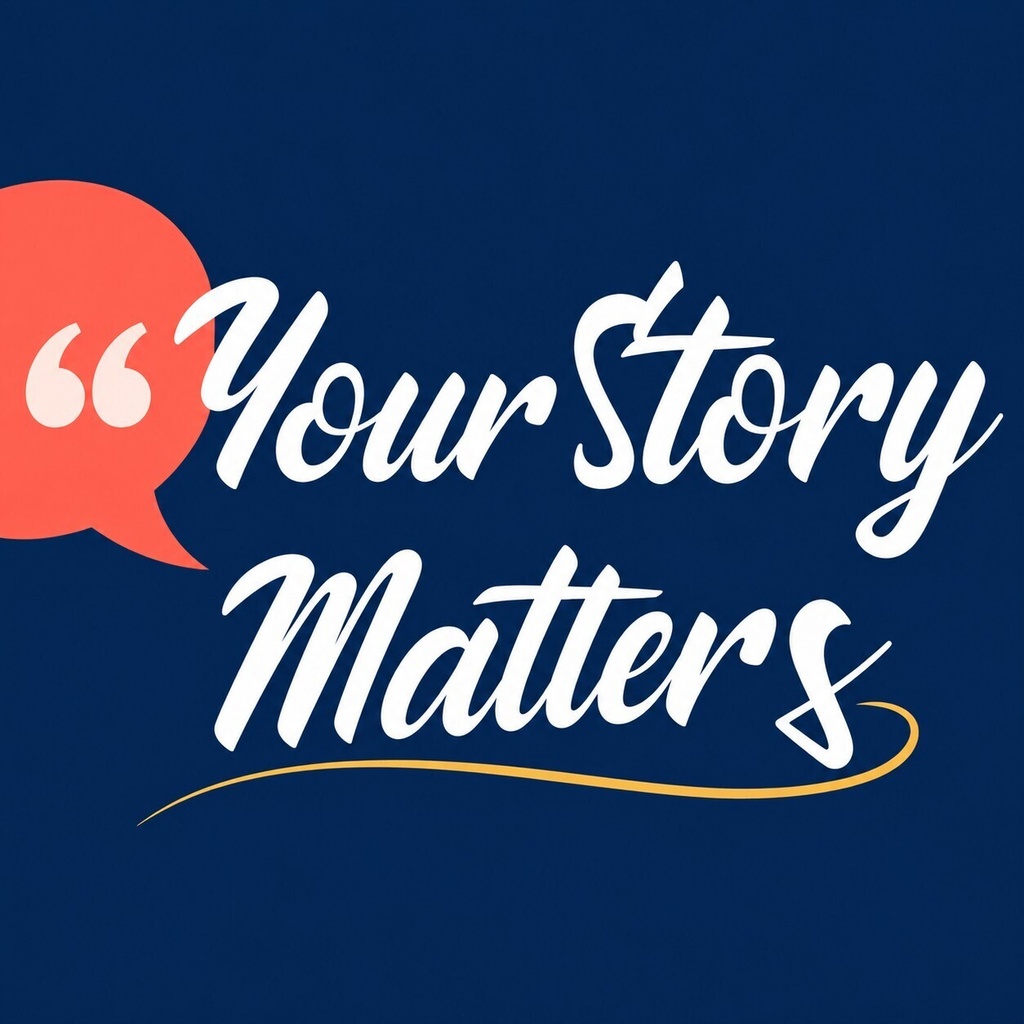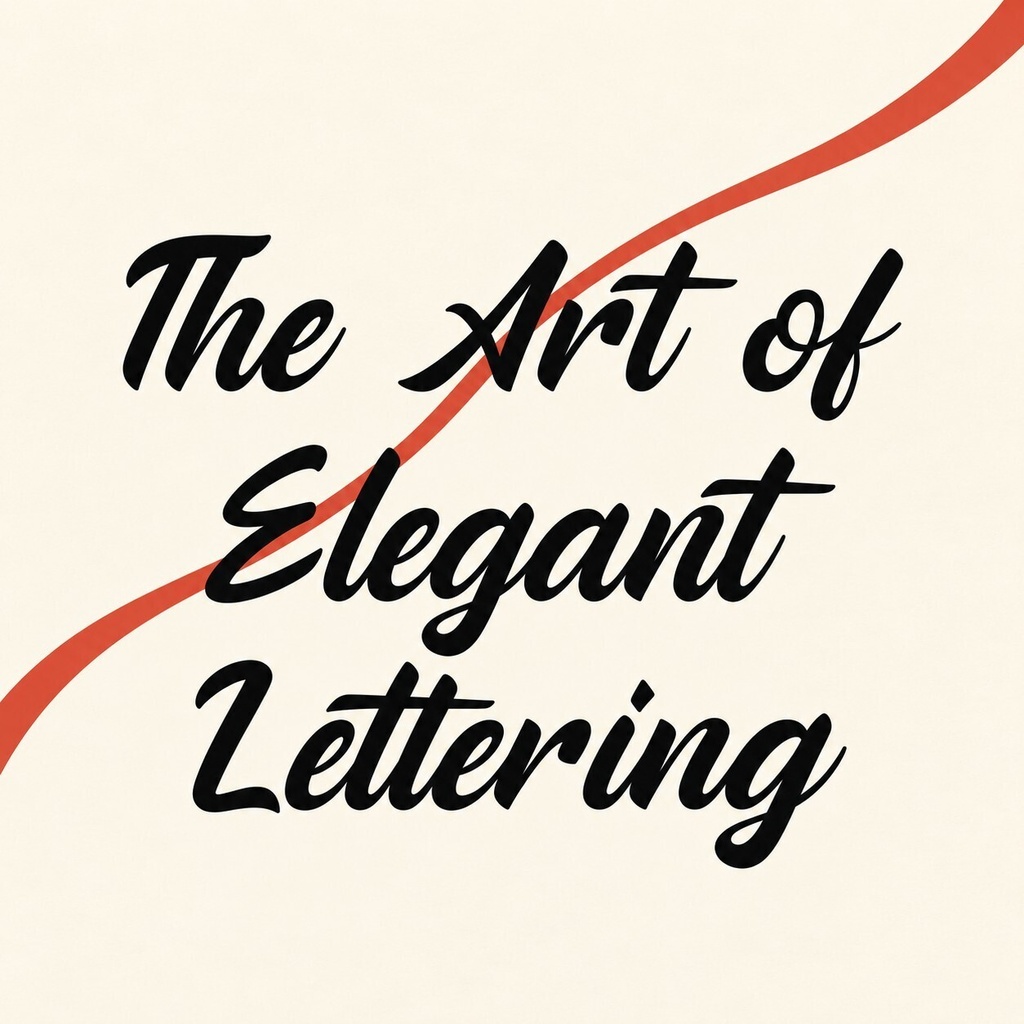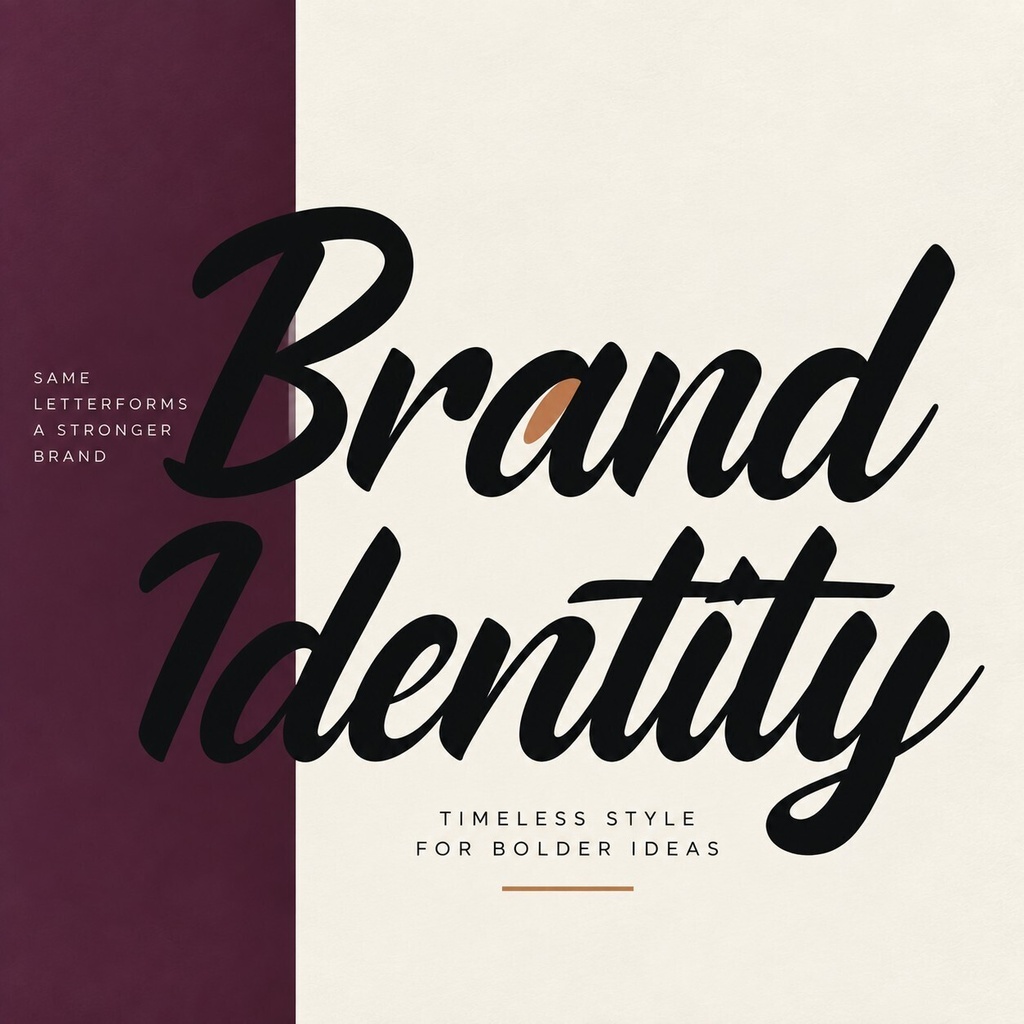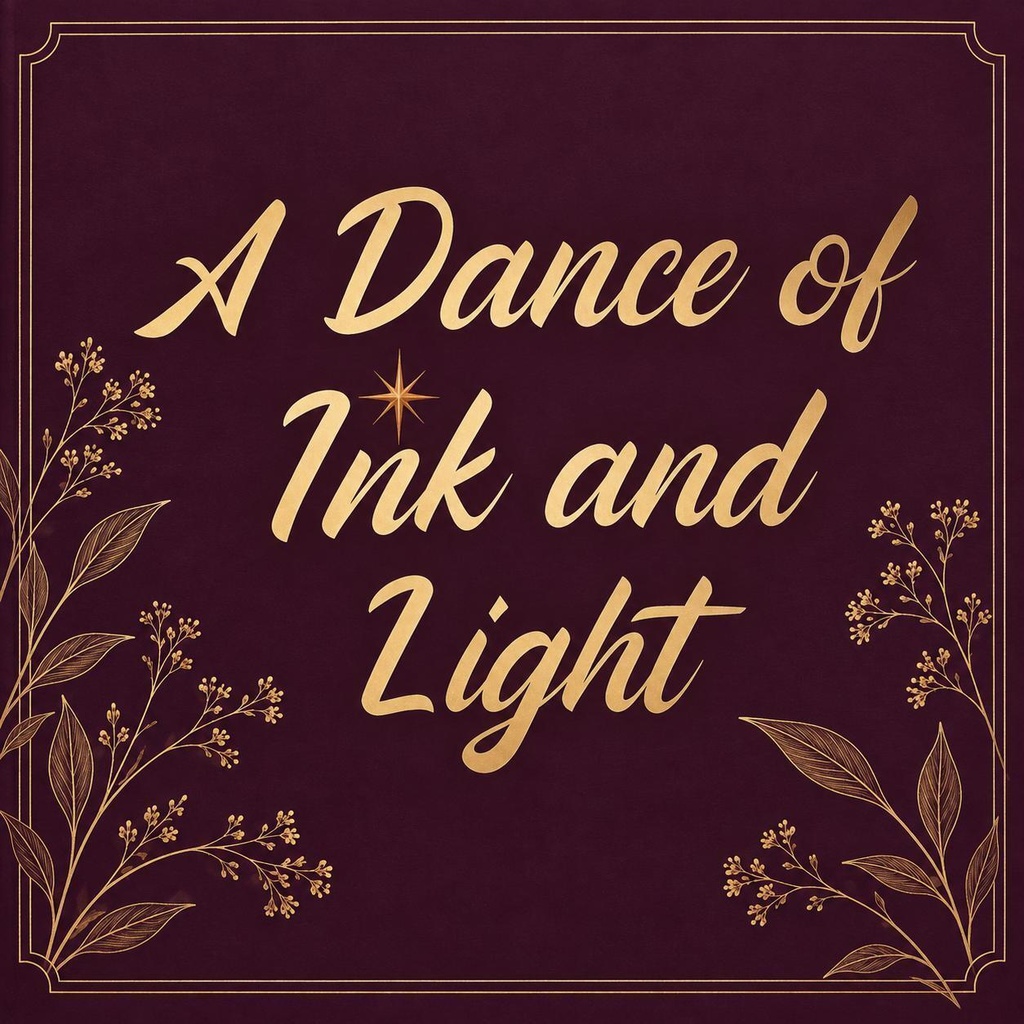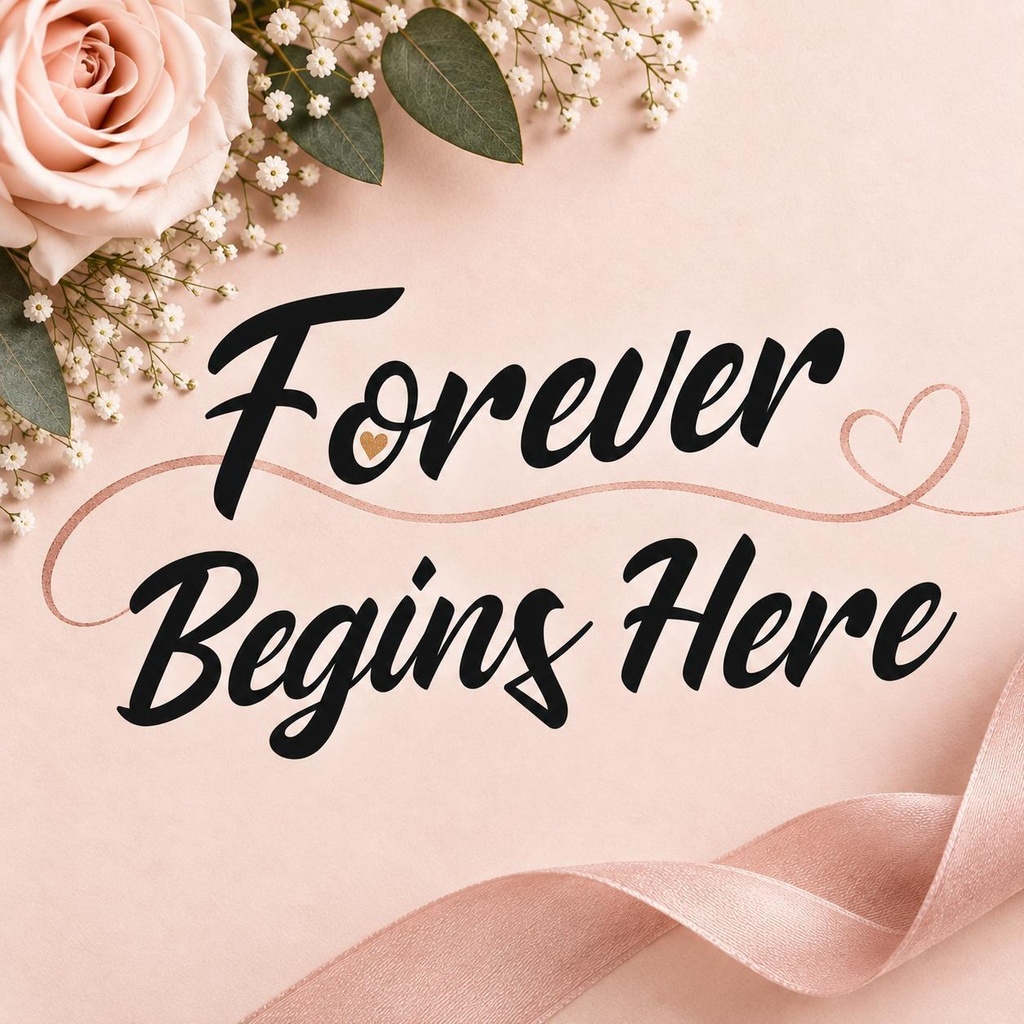
Silken Flourish(シルクン・フローリッシュ)【手書きフォント】
万年筆のような滑らかなストロークと洗練されたフォルムが特徴のエレガントな手書きフォントです。ロゴデザイン・ウェディング招待状・ブランドロゴ・スターショナリー・コスメパッケージ・アパレル・ポスター・見出し・レターヘッド・商品ラベルなど、上品で印象に残るタイポグラフィ制作に最適です。 Silken Flourish は、スムーズでクリーンなラインを活かしたディスプレイ書体です。多言語アクセント文字やスタイリッシュなリガチャーを備え、ロゴやステートメントタイポグラフィで洗練された雰囲気を演出します。 ## 収録内容 - フォントファイル一式(OTF, TTF, WOFF, WOFF2) - 大文字・小文字、数字、記号・句読点 - スタイリッシュセット - リガチャー ## 対応文字 - 英語アルファベット(A-Z, a-z) - 数字(0-9) - 記号・句読点 - スタイリッシュセット・リガチャー ## 用途 - ロゴデザイン・ブランドロゴ - ウェディング招待状・ステーショナリー - コスメパッケージ・ブランドラベル - アパレル・ラベルデザイン - ポスター・見出し・ヘッダー - レターヘッド・タイトルロゴ - ゲームタイトル・ビジュアルロゴ - マーケティング素材・広告 ## 形式 - OTF(OpenType Font) - TTF(TrueType Font) - WOFF(Web Open Font Format) - WOFF2(Web Open Font Format 2) ## 対応環境 - macOS / Windows / Linux - Adobe Photoshop / Illustrator / InDesign - Figma / Sketch / Canva - 主要なグラフィックソフトウェア ## 利用許諾 本フォントは商用利用可能(Commercial Use)です。ロイヤリティフリーで、ビジネス・クライアント向け・有料・ブランド化・広告・グッズ制作に使用できます。個人利用(Personal Use)版は、購入者自身の非商用プロジェクト・学習・練習・プライベート制作に使用できます。詳細は付属のライセンスファイルをご確認ください。